Sebastien Cuypers es diseñador gráfico y ilustrador francĂ©s el cual hace una mezcla perfecta entre los diferentes motivos de sus ilustraciones y la tipografĂa.
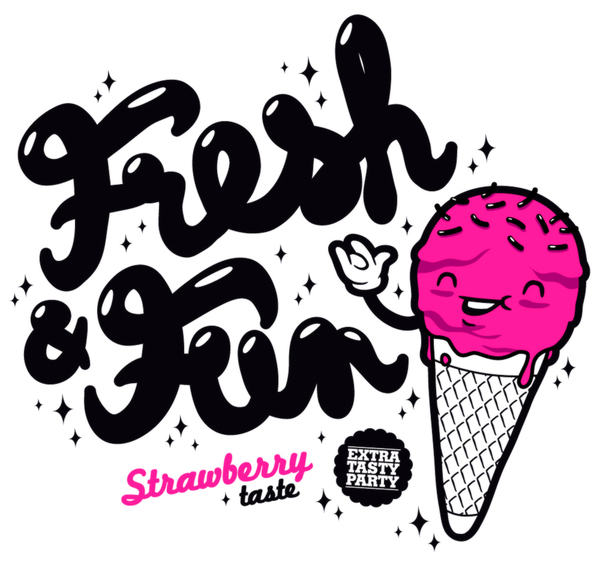
Sebastien Cuypers es diseñador gráfico y ilustrador francĂ©s el cual hace una mezcla perfecta entre los diferentes motivos de sus ilustraciones y la tipografĂa.